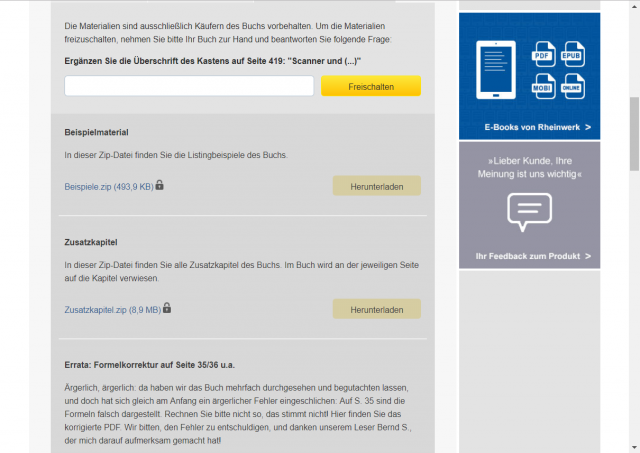
[Buch] Mediengestaltung Der Ausbildungsbegleiter
zum aufrischen und lernen gleichermaßen gut geeignet.
Im Bild kann man gut erkennen dass man auch Begleitmaterial downloaden kann.
Hier finde ich clever, dass man dieses Material nur freischalten kann wenn man auch das Buch hat.
Die Abfrage wird ständig verändert .
Ich habe mit dem Rheinwerk-Verlag Kontakt aufgenommen. Demnächst kommt für Typografie.info eine Leseprobe für den Abschnitt 6.1-6.4 mit Inhaltsverzeichnis als Leseprobe.  also das spezielle Thema Typografie.
Vorab kann ja jeder schon mal sehen welche Themen es gibt. 6.1-6.4 wird als PDF bereitgestellt, quasi wie die normale Leseprobe auf der Webseite siehe oben.
Ja die FF DIN ließst sich richtig gut auf Tablet(te) ;-) und Papier. um den Spagat hinzubekommen (Seitenzahl/Preis) haben sie 90g/m² Papier genommen. Das ist selbst in der Qualität (Papier und Druck) völlig ausreichend. Ich würde auf einer Skala von 1-10 eine 9.9 geben.
Auf S. 35/36 von Mediengestaltung sind denen ziemlich peinliche Fehler bei den Umrechnungsformeln zwischen Pixeln, dpi und Zentimetern passiert. Die stimmen allesamt nicht. Das ist aber immer das Problem bei so dicken Schwarten. Die werden doch oft etwas mit der heißen Nadel gstrickt. Abgesehen davon ist der Titel umfassend, interessant, für die Fülle an Informationen günstig und zudem noch buchbinderisch hervorragend verarbeitet (Hardcover mit Fadenheftung), was man von Typografie für alle leider nicht behaupten kann. Das ist inhaltlich zwar, wie erwartet, super, aber Softcover mit einer zudem noch sehr störrischen Klebebindung. Schade.
Solche eine lieblose Verarbeitung war ich von Rheinwerk gar nicht gewohnt.
Sagt mal hier sind ja richtige Profies online, die Ja sofort beim querlesen sehen, dass dieses Buch gravierende Fehler beinhaltet. Ich hatte mir dieses Buch ja extra gekauft um noch mal einen IHK Abschluss zu machen.
Ich bin durch die Neue Qualität von RheinwerkVerlag etwas verunsichert.
Mir ist es ja Anfang der 90er schon so gegangen, dass ich erst im Praktikum darauf hingewiesen wurde dass, was wir gelernt hatten füllig und völlig falsch ist.
gibt es denn sowas wie Qualitätssiegel für Fachbücher?
Gemeint ist das Buch hier
Ich hatte ja vorgeschlagen, wenigstens die PDF zu bereinigen. Auch das ist bis jetzt nicht erfolgt.
Nun wer in der Theorie lernt die Farben RGB sind Gelb Zyan Magenta (nein nicht wirklich so gelernt) aber nur als Beispiel wird sich, wenn es ersteinmal im Kopf drin ist schwer haben das gelernte und gefestigte wieder loszuwerden un wieder umzudenken etc.